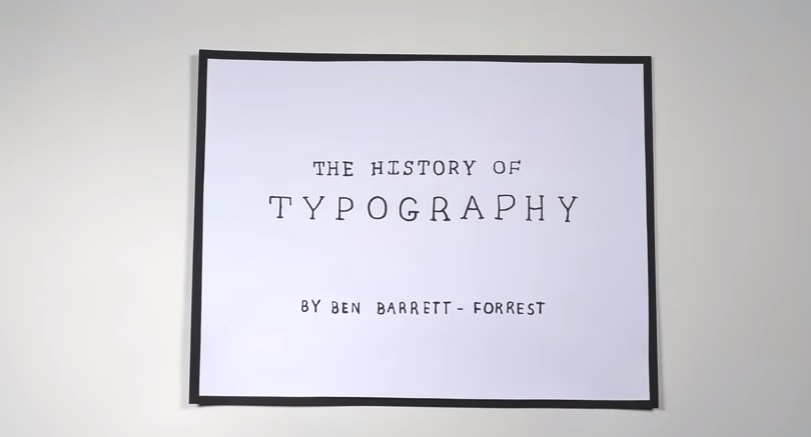
Quiero compartir con ustedes un corto animado en Stop Motion que nos relata de manera sobria e interesante la historia de la tipografía; Un recurso necesario y que todo diseñador o creativo debe de tenerse siempre presente; ya que al fin y al cabo sin las letras no podríamos llevar nuestros mensajes al mundo.